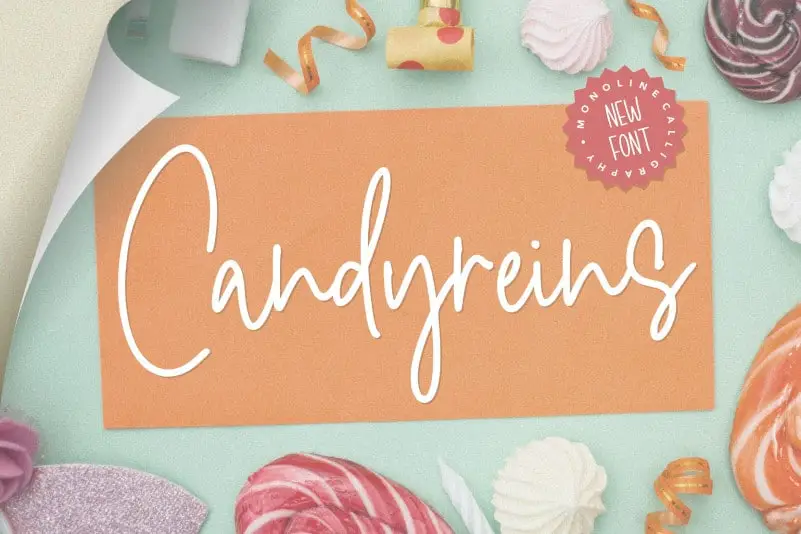
Candyreins Monoline Calligraphy Font – Download Grátis
A Candyreins Monoline Calligraphy Font é perfeita para adicionar um toque elegante a qualquer projeto visual. Seja ele para embalagens de produtos, marcas de marca, revistas, redes sociais, ou até mesmo para destacar frases em eventos como casamentos, esta fonte traz uma sensação delicada e sofisticada aos seus materiais. Com seu estilo elegante e linhas finas, Candyreins Monoline Calligraphy é perfeito para quem busca uma fonte que ofereça o equilíbrio entre modernidade e elegância. Perfeita para aqueles momentos em que você deseja dar um destaque especial aos seus textos, seja no topo de um rosto ou em um fundo neutro. Ideal tanto para designers gráficos quanto para profissionais de mídia social que buscam uma fonte chamativa e elegante, Candyreins Monoline Calligraphy é a escolha certa para aqueles projetos que desejam trazer um ar sofisticado ao seu trabalho.